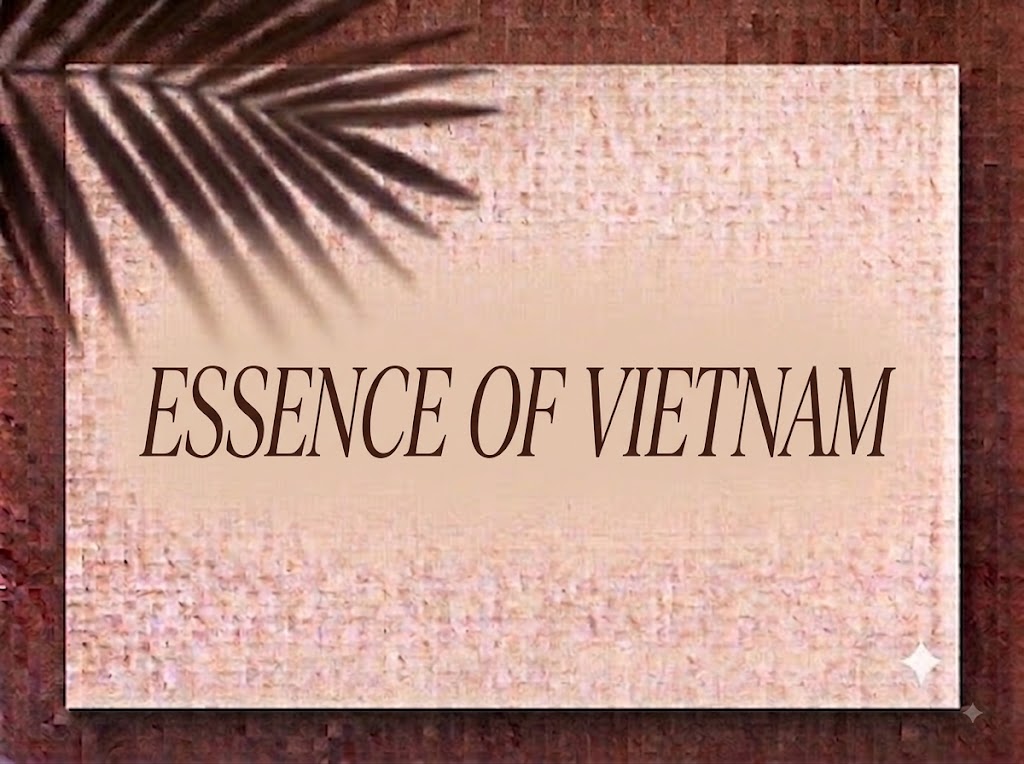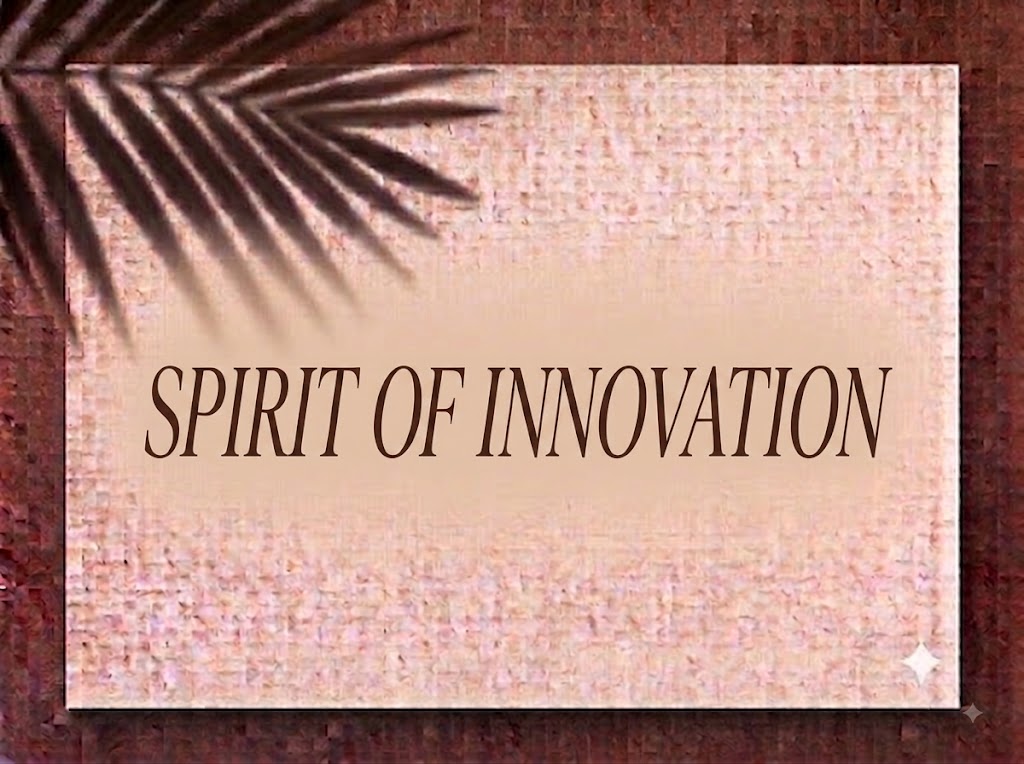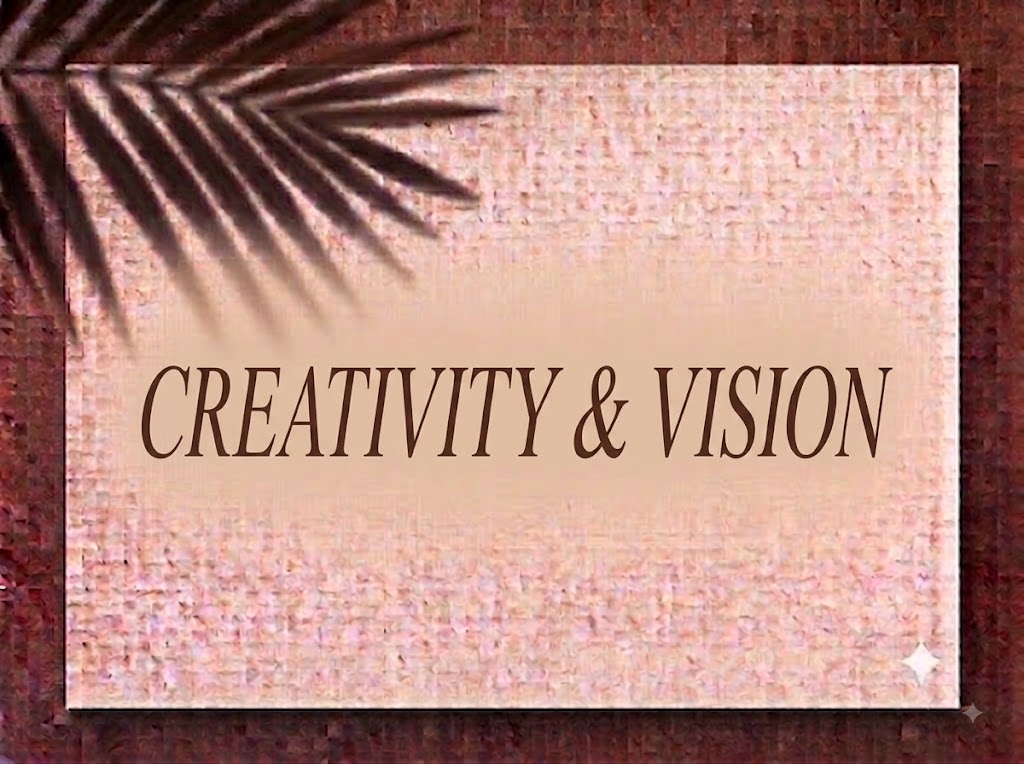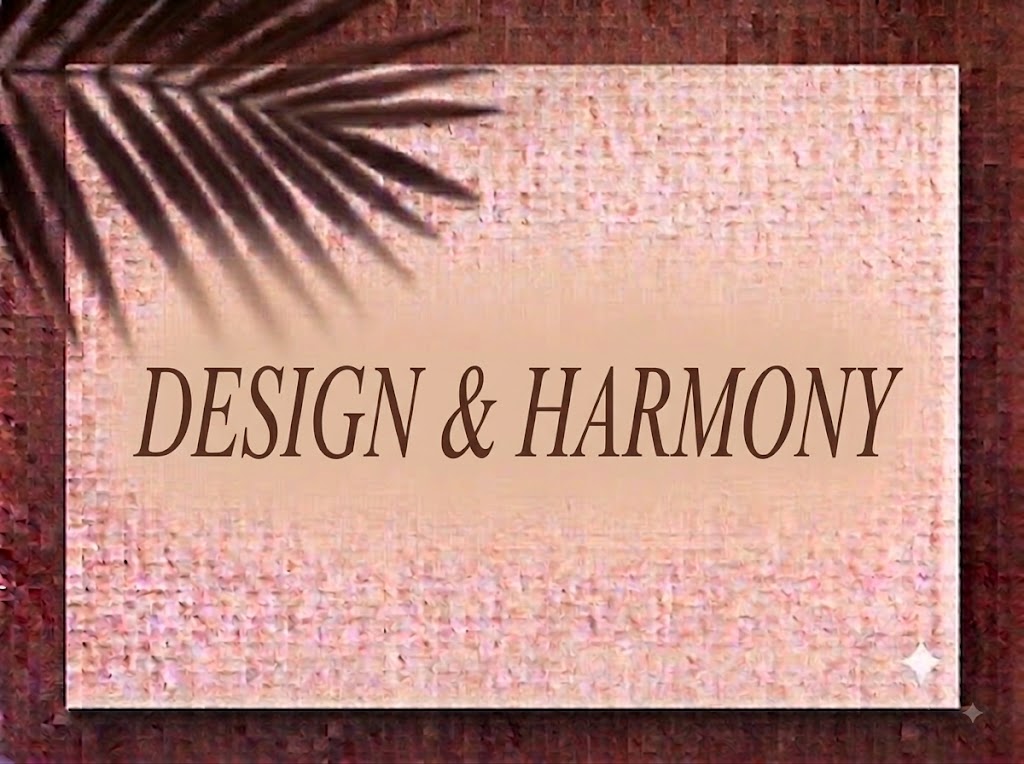
1FTV VIP Casselin
Trong thiết kế truyền thông cao cấp, ngành thời trang, mỹ phẩm và các thương hiệu phong cách sống, việc lựa chọn một phông chữ hiển thị sở hữu vẻ đẹp kiều diễm, nhẹ nhàng nhưng tràn đầy thần thái sang trọng là yếu tố then chốt. Một tiêu đề tinh tế không chỉ truyền tải thông điệp ngắn gọn mà còn lập tức nâng tầm đẳng cấp thị giác cho toàn bộ ấn phẩm.
Nếu bạn đang tìm kiếm một phông chữ Display Serif thanh thoát, sở hữu các đường nét tương phản mềm mại cho bìa tạp chí, lookbook, logo spa hay tiêu đề video ngắn, font 1FTV VIP Casselin chính là sự lựa chọn không thể bỏ qua.
Giới thiệu về font 1FTV VIP Casselin
Font 1FTV VIP Casselin là bộ chữ hiển thị có chân (display serif) mang phong cách tân cổ điển hiện đại, nổi bật với sự giao thoa giữa cấu trúc chữ thanh mảnh và những nét uốn cong tinh tế:
Tên phông chữ: 1FTV VIP Casselin
Nhờ nền tảng kỹ thuật chỉn chu, phông chữ đem lại khả năng hiển thị vô cùng sắc nét. Bạn có thể tự tin phóng lớn tiêu đề trên các phần mềm đồ họa chuyên nghiệp hay ứng dụng dựng video di động mà không lo bị vỡ nét hay răng cưa.
Đặc điểm nổi bật của phong cách thiết kế VIP Casselin
Sức hút thị giác của font 1FTV VIP Casselin đến từ phom dáng thanh mảnh, vươn cao cùng độ tương phản nét cực kỳ nghệ thuật:
Nét tương phản thanh đậm dịu dàng: Sự chênh lệch giữa cột nét dọc thanh thoát và các đường cong mỏng nhẹ mang lại chiều sâu nghệ thuật kiều diễm, gợi liên tưởng đến các thương hiệu thời trang và mỹ phẩm cao cấp.
Phom dáng vươn cao kiêu kỳ: Các ký tự có tỷ lệ chiều cao ấn tượng cùng phần nét kéo dài nhẹ nhàng ở các ký tự như
f,j,g,q,y, giúp câu tiêu đề vừa tiết kiệm không gian chiều ngang vừa giữ được vẻ đài các. -
Đồng bộ chữ hoa và chữ thường: Bộ chữ cái in hoa vững chãi kết hợp cùng dàn chữ thường mềm mại, giúp các designer linh hoạt phối hợp phân tầng nội dung tự nhiên.
Khoảng cách giữa các chữ (kerning) và độ giãn dòng được tính toán chuẩn xác, giúp các nét chữ mảnh khi đứng sát nhau không bị dính nét hay rối mắt.
Tích hợp trọn vẹn bộ chữ cái hoa – thường, dãy chữ số 0-9 dáng đứng thanh lịch cùng hệ thống ký tự đặc biệt, dấu câu thông dụng.
Bản Việt hóa chuẩn chỉnh giúp bạn hoàn toàn yên tâm thiết kế các văn bản tiếng Việt có dấu mà không gặp lỗi nhảy font hay mất ký tự.
Hình ảnh demo thực tế của font 1FTV VIP Casselin
Khả năng hiển thị của phông chữ này được tối ưu rất tốt trên nhiều tỷ lệ kích thước khác nhau:
Kích thước nhỏ (12pt – 24pt): Cấu trúc chữ đứng ngay ngắn và khoảng hở nội tại thông thoáng giúp các câu chữ và dãy số vẫn hiển thị rõ ràng trên màn hình di động.
Kích thước lớn (36pt – 72pt): Đây là đất diễn lý tưởng nhất để 1FTV VIP Casselin phô diễn toàn bộ sự kiêu sa, quyến rũ của các đường nét thanh mảnh, tạo tác động thị giác mạnh mẽ cho các dòng tiêu đề chính.
Ứng dụng trong thiết kế đồ họa và làm video
Sở hữu nét cá tính thanh lịch và giàu tính nghệ thuật, font 1FTV VIP Casselin mở ra không gian ứng dụng phong phú:
Video ngắn (TikTok, Reels, Shorts): Phông chữ serif dáng cao này hiển thị rất đẹp trên khung hình đứng tỷ lệ 9:16. Cực kỳ ăn nhập với các video vlog thời trang, review mỹ phẩm, trang sức, spa hay phong cách sống nghệ thuật.
Ảnh thu nhỏ YouTube (Thumbnail): Lựa chọn tuyệt vời cho các kênh làm nội dung về thời trang, làm đẹp, âm nhạc lofi, acoustic hoặc review đồ hiệu nhờ giao diện chuyên nghiệp và thu hút.
Thiết kế Bìa Tạp chí, Lookbook và Poster: Hoàn hảo cho các sản phẩm truyền thông thuộc lĩnh vực thời trang thiết kế, spa, mỹ phẩm, triển lãm nghệ thuật hay thương hiệu váy cưới.
Nhận diện thương hiệu phân khúc Luxury: Thích hợp làm logo dạng chữ, bao bì nước hoa, menu nhà hàng/khách sạn 5 sao hay thiệp mời sự kiện VIP.